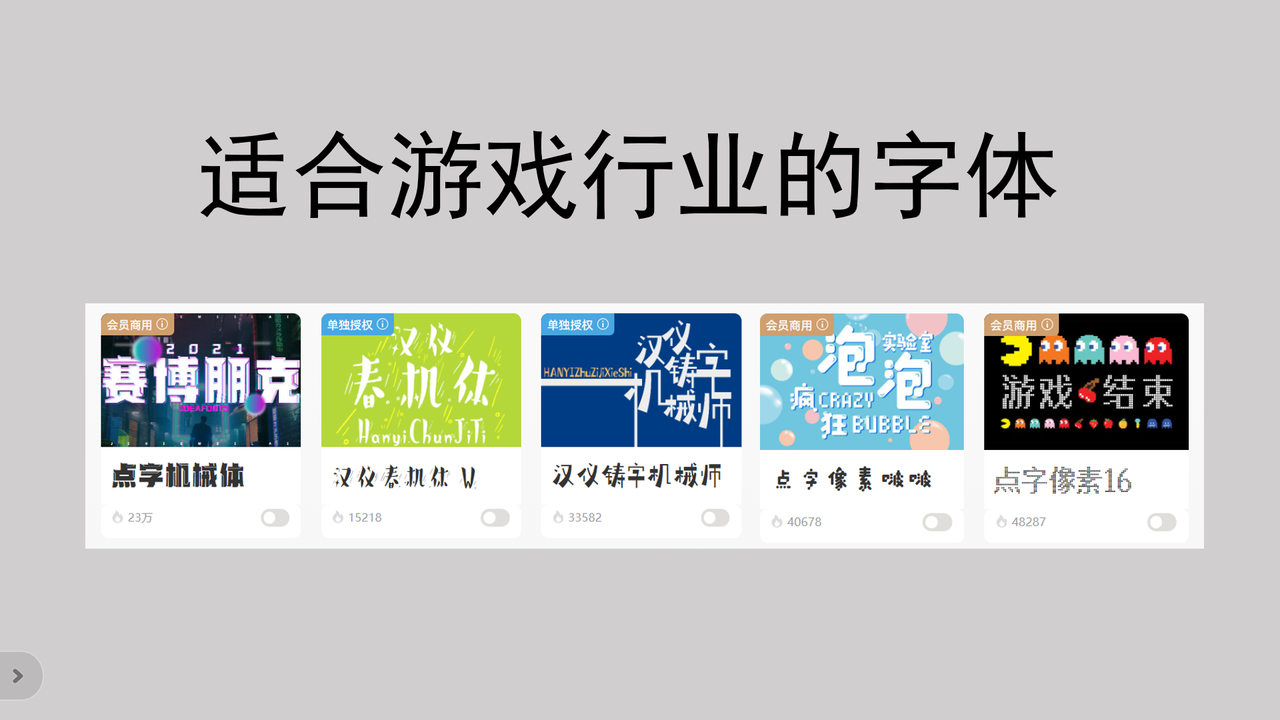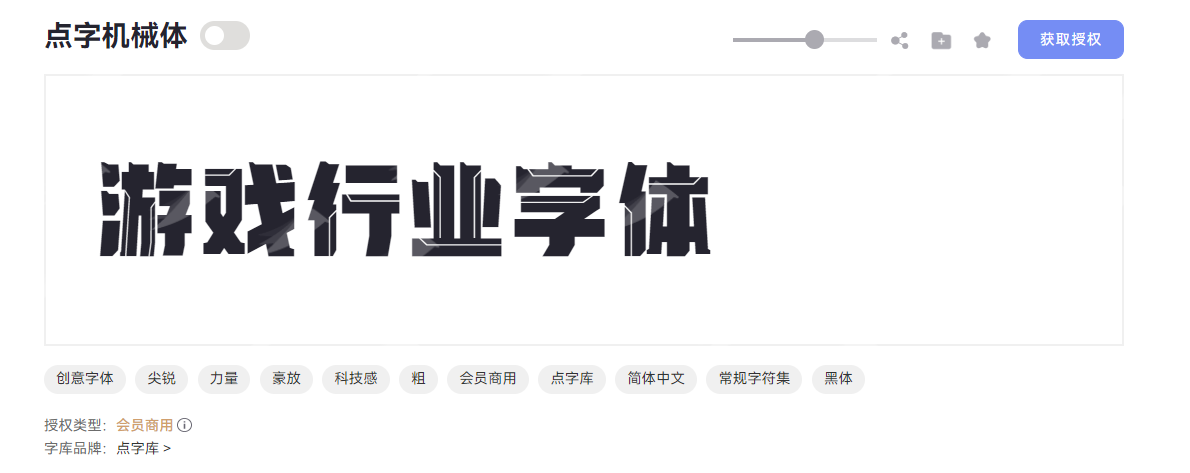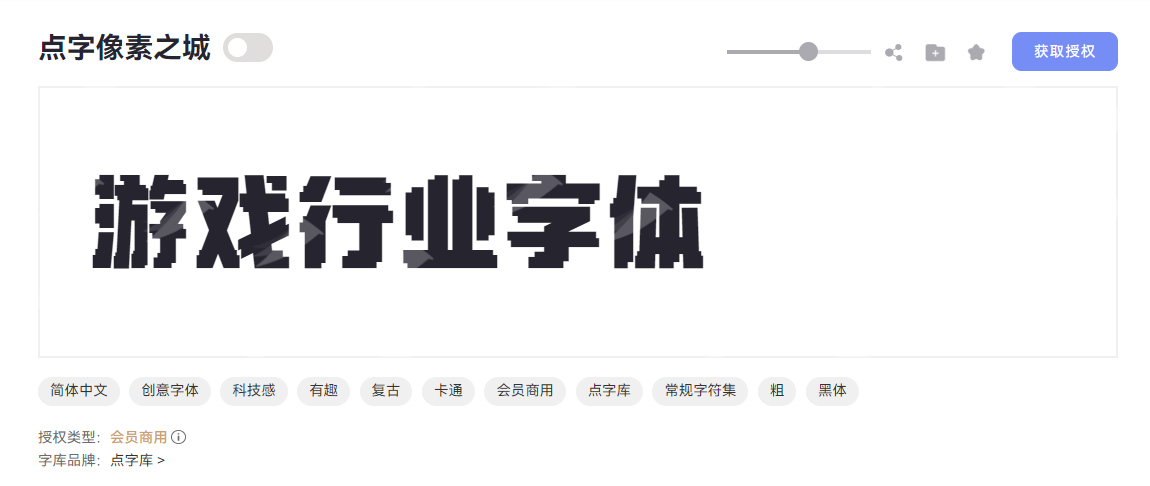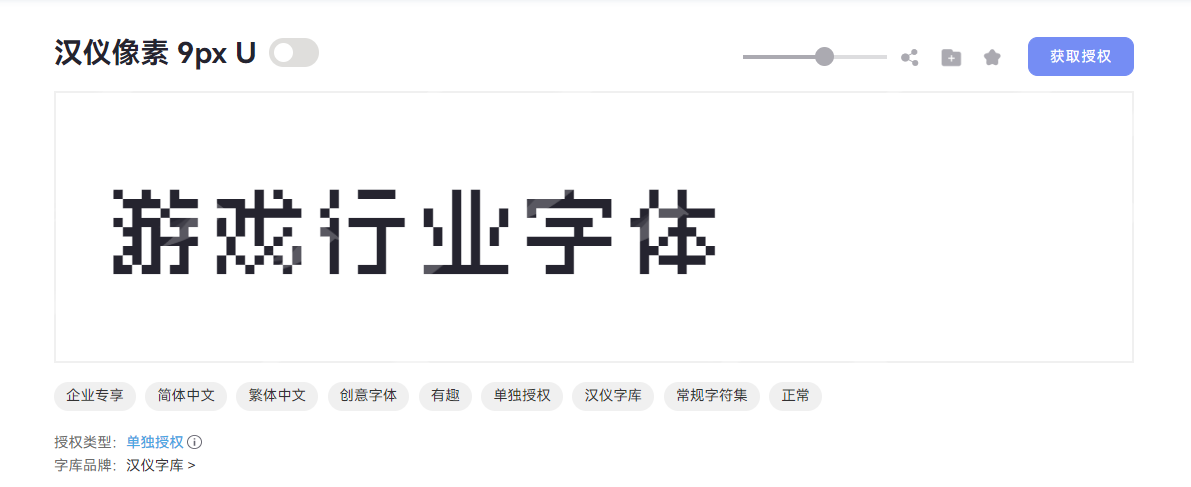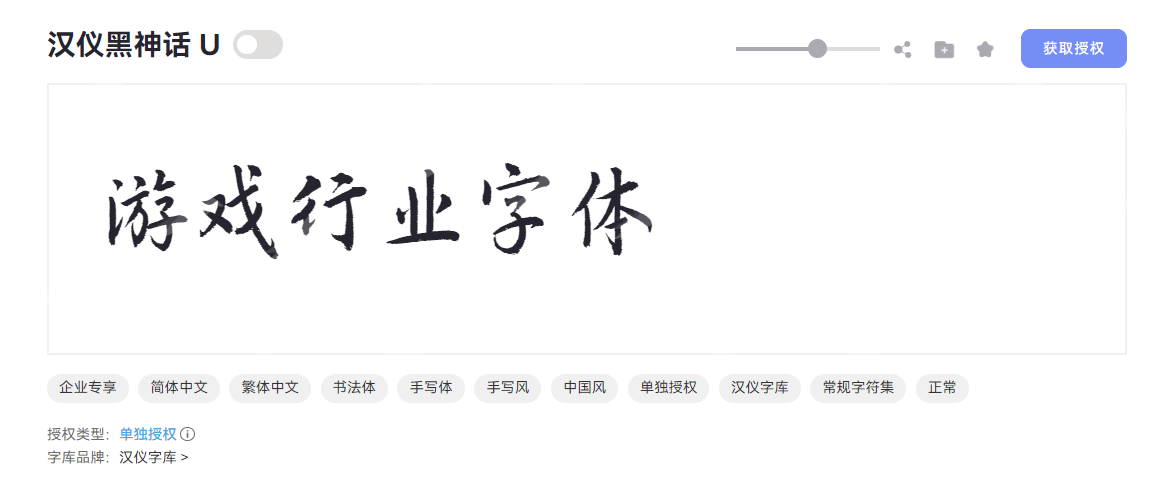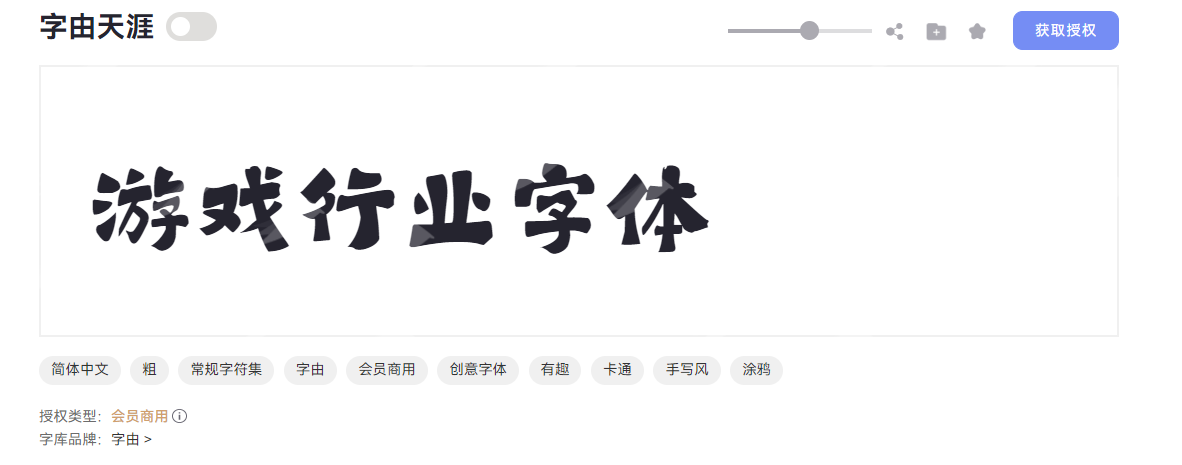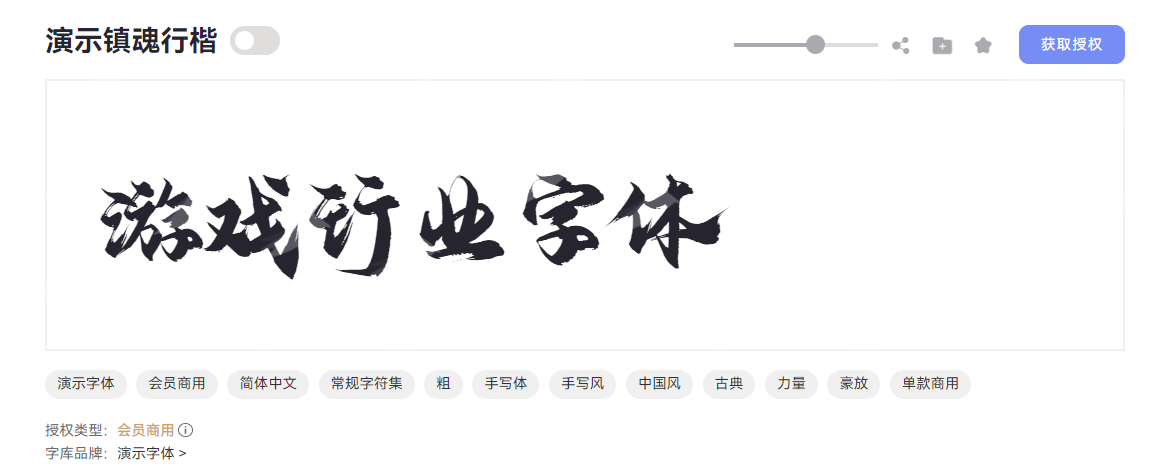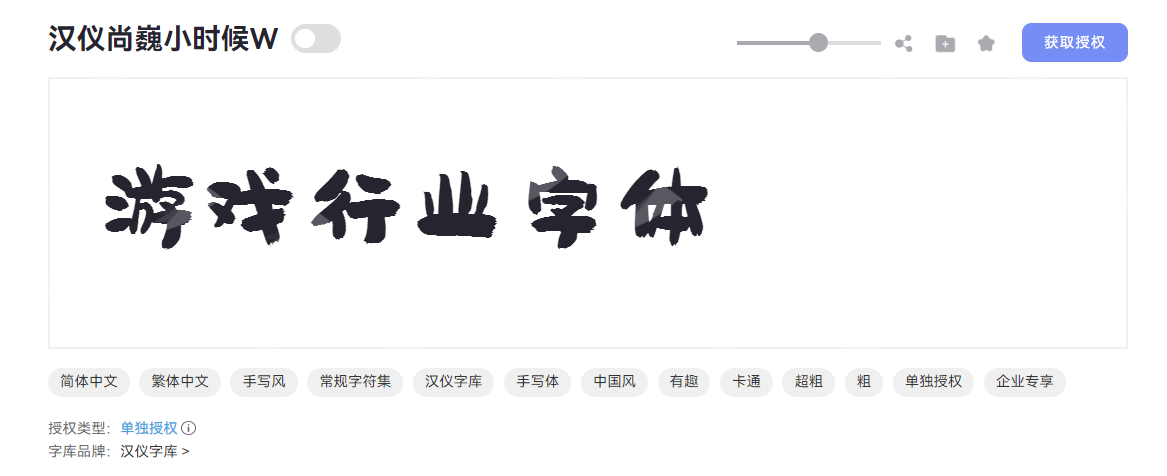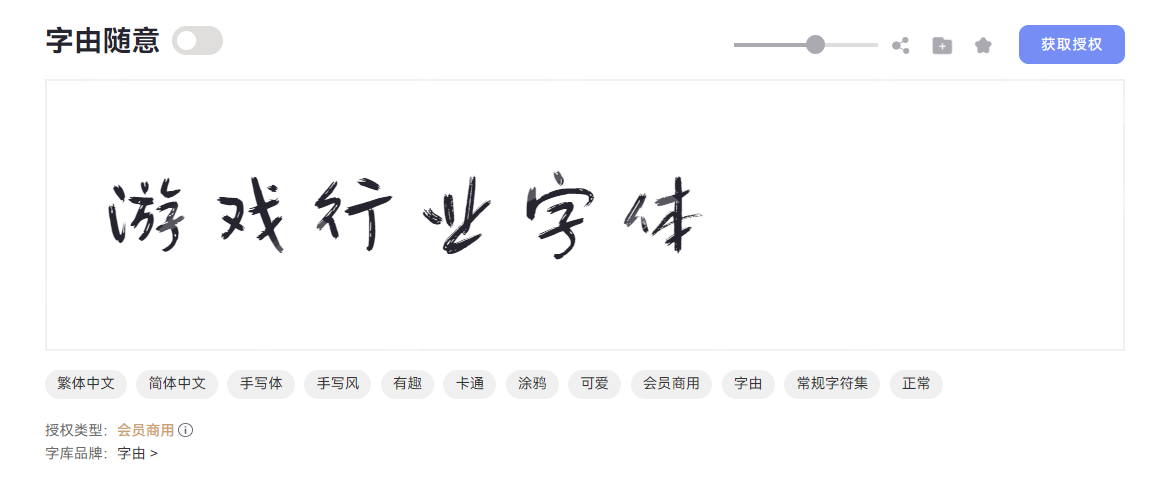
游戏设计师必备!适合游戏行业的高质量字体大全
在游戏行业,字体设计也是非常重要的一环,因为它不止是传递信息的作用,它还是游戏世界观的一部分。选择一款适合游戏行业的字体,能增加玩家的沉浸感和体验感,也能让游戏画面更加和谐自然。然而,面对市面上海量的字体资源,如何找到符合游戏风格又能商用的字体?本文将以字由官网为出发点,按照游戏类型分类汇总,为大家推荐几款适合游戏行业的高质量字体。无论你在制作什么类型的游戏,这份字体大全都能帮你快速找到最合适的那一款。
一、科幻机甲类
点字机械体和机甲战斗类的游戏、赛博朋克风格的游戏适配度 100%。字形结构采用更加能体现机械感的正方形为框架进行设计,竖划的起笔凸起处理以及收笔的切角处理外加的撇捺的出笔,共同构成字形的鲜明个性;笔画厚重,棱角分明,粗壮稳健,富有庄重感;字形结体严谨,点画硬朗。点字机械体运用线性镂空来增强字体的立体感,确保玩家只要看见这款字体,就能感受到那股金属机械的凛冽感与未来感。
二、复古像素类
点字像素之城
点字像素之城是由点字库打造的创意字体,以复古像素风为核心,融合卡通趣味与科技质感,成为游戏界面设计的理想选择。字体结构修长,重心偏高,中宫宽博设计确保字形端正、识别度优异;笔型以像素点为基本单元拼合,方头笔画搭配均匀粗细线条,连接处以颗粒感断开,既保留 8-bit 复古游戏的方块美学,又通过像素颗粒传递灵动趣味。无论是打造怀旧主题效果的游戏,还是凸显科技潮流风格的游戏,这款字体都能以独特像素语言赋予作品吸睛表现力。
汉仪像素 9px
汉仪像素 9px 是一款像素风格的中文字库,大小为9x9像素,适合用在复古游戏机上。常规的像素字体仅留有 1 像素的间距,而这款字体左右各保留 1 像素的间距,即 2 像素的间距,以此来优化排版效果。在字体设计方面,汉仪像素体采用黑体的设计思路,笔画更加简洁明朗,布白均匀,灰度平衡。注重轮廓的保留和线条的流畅,采取避让、合并、精简的方式,使整体更贴近常规字形,同时具有强烈的像素风格。
三、武侠国风类
汉仪黑神话
汉仪黑神话是汉仪字库联合游戏科学研发团队开发的一款笔法凌厉的行楷书法字体,是为《黑神话:悟空》量身定制的。这款字体的笔画硬朗,风格刚柔并济,完美贴合了武侠国风类游戏的整体调性。关于设计灵感,汉仪黑神话的书写风格参考了书法大家欧阳询,字形险绝峭拔,千形万象,一字多形,提供多种字形选择。另外,该字体优化了纵向书写,符合游戏内置版面的章节回合、人物铭牌、建筑名称、道具名称、菜单栏等排版应用,有更佳的展示效果。
字由天涯
如果你近期正在制作一款拥有江湖侠气的游戏,千万不要错过字由天涯——一款带有浓郁“江湖”色彩的创意书法字体。虽然属于书法字体,但它并没有楷书看起来规整,也不是草书的狂放不羁,更像是一种行走于江湖的随性字体。字由天涯体的笔刷效果是在模拟衣袖飞扬的感觉,笔画之间有轻微断连,笔画边缘趋于圆润,带着点可爱的感觉,又带着豪放洒脱的气质。当玩家看到这款字体用于书写江湖门派标识、游戏内书信或秘籍、又或者是武侠游戏的章节标题等场景,应该会瞬间感受到侠气与不羁的视觉体验,有种置身于游戏内江湖场景的身临其境感。
演示镇魂行楷
演示镇魂行楷是一款力量感的国风字体,适合用于国风游戏的标题、古风游戏 UI 界面等场景,传递出真实书写时的笔墨温度。该字体采⽤纯板绘手写 + 部首笔画拼字合成,光部首制作就写了超过 1000 字。字体结构上保留了大笔触与⻜⽩,其中部分笔画为反笔,尊重传统书法结构,尽量让每个字都美观。
四、可爱治愈类
汉仪尚巍小时候
汉仪尚巍小时候是一款充满童真与怀旧情感的手写字体,由汉仪字库与设计师尚巍共同打造。该字体以其独特、不加修饰的笔触,模仿了孩童时代纯真烂漫的笔迹,旨在唤醒人们心中对于童年美好时光的记忆。它将那份不完美的可爱、不经意的稚拙,转化为数字时代可用的视觉语言,如果把它放进治愈经营类游戏,可以为游戏作品注入温暖、亲切和一丝不羁的个性,最终呈现效果极佳!
字由随意
字由随意是字由品牌推出的一款手写体字体,融合卡通、可爱、手写风与涂鸦趣味,以轻松灵动的笔韵传递自由活泼的视觉感受。作为专为创意场景打造的手写字体,其字重正常却粗细均匀,粗实笔画中透着随性与活力,仿佛手写时的即兴创作,字里行间跳跃着自由的韵律,很适合放进一些轻松简单的可爱风小游戏里,营造活泼有趣的视觉氛围。 字由随意在结构设计上兼具方正形态与宽博中宫,重心居中的排布让字体既稳定又舒展;笔型融入俏皮斜切设计,方头笔画搭配自然断开的笔触,打破传统手写体的规整感,每一笔都似随手涂鸦般生动,卡通感与手写温度并存。